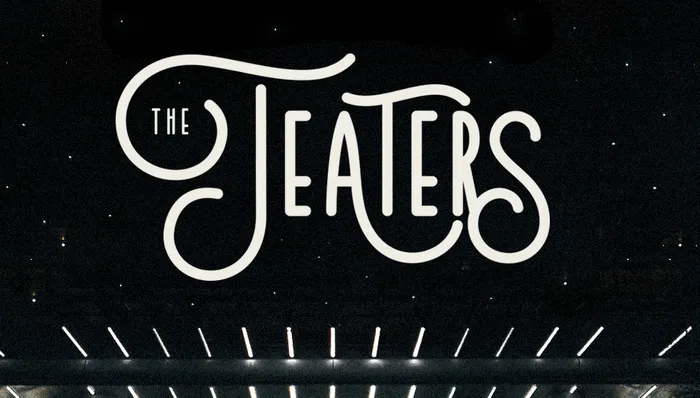
Introduzimos Teaters Typeface, inspirado nos teatros de grande porte que frequentemente abrigam grandes apresentações de circo ou espetáculos musicais. Este tipo casual de sans serif oferece alternativas únicas e suporte a múltiplas línguas. O Teaters Typeface permite que você crie um texto com aparência artesanal, tornando-o uma escolha ótima para projetos gráficos como cartazes, identidade visual, flyers, cartões de visita, convites e até mesmo trabalhos de escrita. Este tipo é perfeito para quem procura algo moderno, sofisticado e único para seus projetos design, que vão além da simples estética tradicional do sans serif. Seja para uma campanha de marketing digital ou a criação de um logotipo inovador, Teaters Typeface tem o poder de transformar qualquer projeto em destaque na sua página.